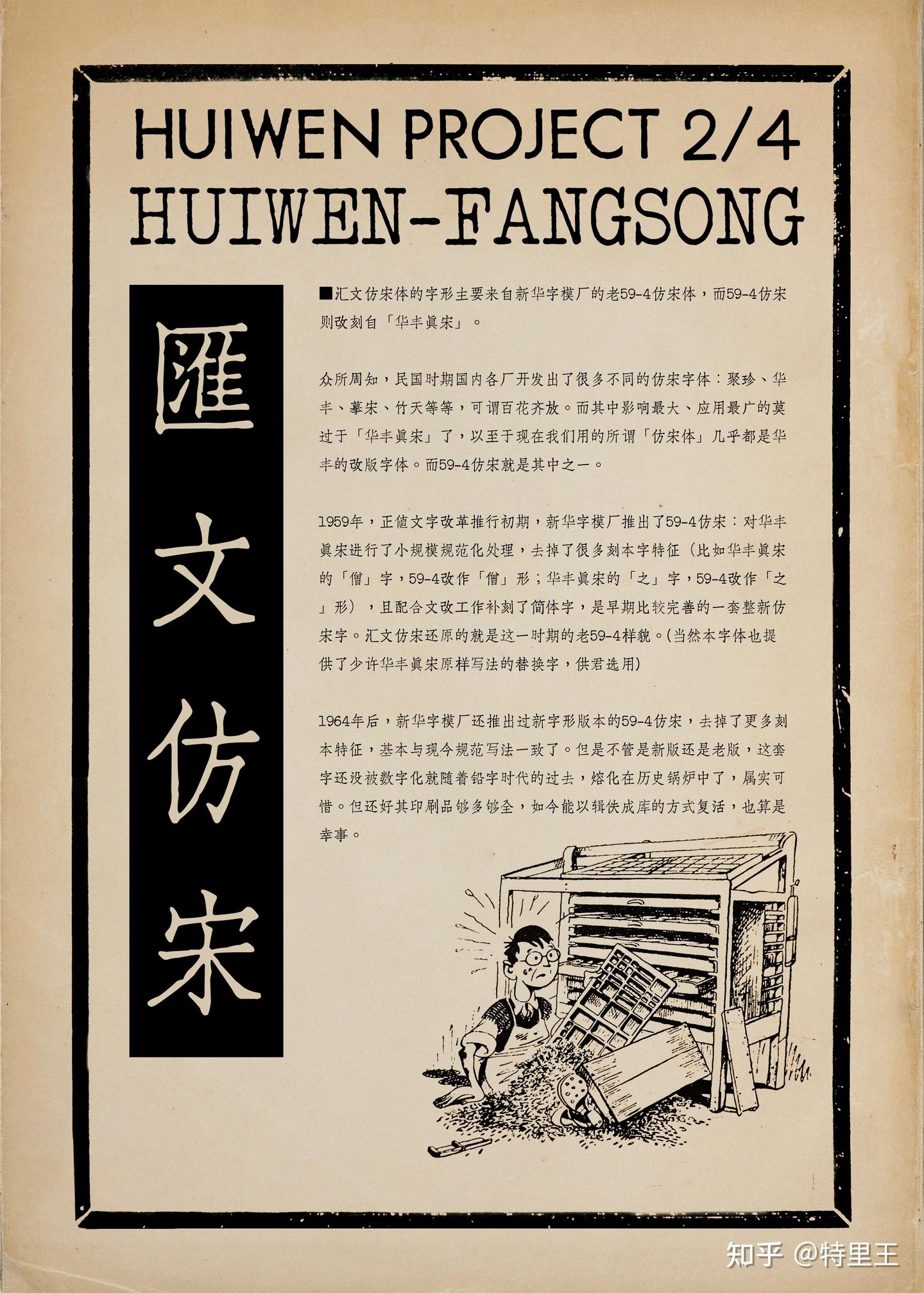
汇文仿宋体是一款由网友特里王发布的一款免费商用的中文复古印刷字体,该字体为汇文系列(仿楷黑明)之仿宋体。该字体的字形主要来自新华字模厂的老59-4仿宋体,而59-4仿宋则改刻自 「华丰眞宋」。
# 补充知识:
众所周知,民国时期国内各厂开发出了很多不同的仿宋字体:聚珍、华丰、摹宋、竹天等等,可谓百花齐放。而其中影响最大、应用最广的莫过于「华丰眞宋」了,以至于现在我们用的所谓「仿宋体」几乎都是华丰的改版字体。而59-4仿宋就是其中之一。
1959年,正值文字改革推行初期,新华字模厂推出了59-4仿:对华丰眞宋进行了小规模规范化处理,去掉了很多刻本字特征(比如华丰眞宋的「僧」字,59-4改作「僧」形;华丰眞宋的「之」字,59-4改作「之」形),且配合文改工作补刻了简体字,是早期比较完善的一套整新仿宋字。汇文仿宋还原的就是这一时期的老59-4样貌。(当然本字体也提供了少许华丰眞宋原样写法的替换字,供君选用)
1964年后,新华字模厂还推出过新字形版本的59-4仿宋,去掉了更多刻本特征,基本与现今规范写法一致了。但是不管是新版还是老版,这套字还没被数字化就随着铅字时代的过去,熔化在历史锅炉中了,属实可惜。但还好其印刷品够多够全,如今能以辑佚成库的方式复活,也算是幸事。